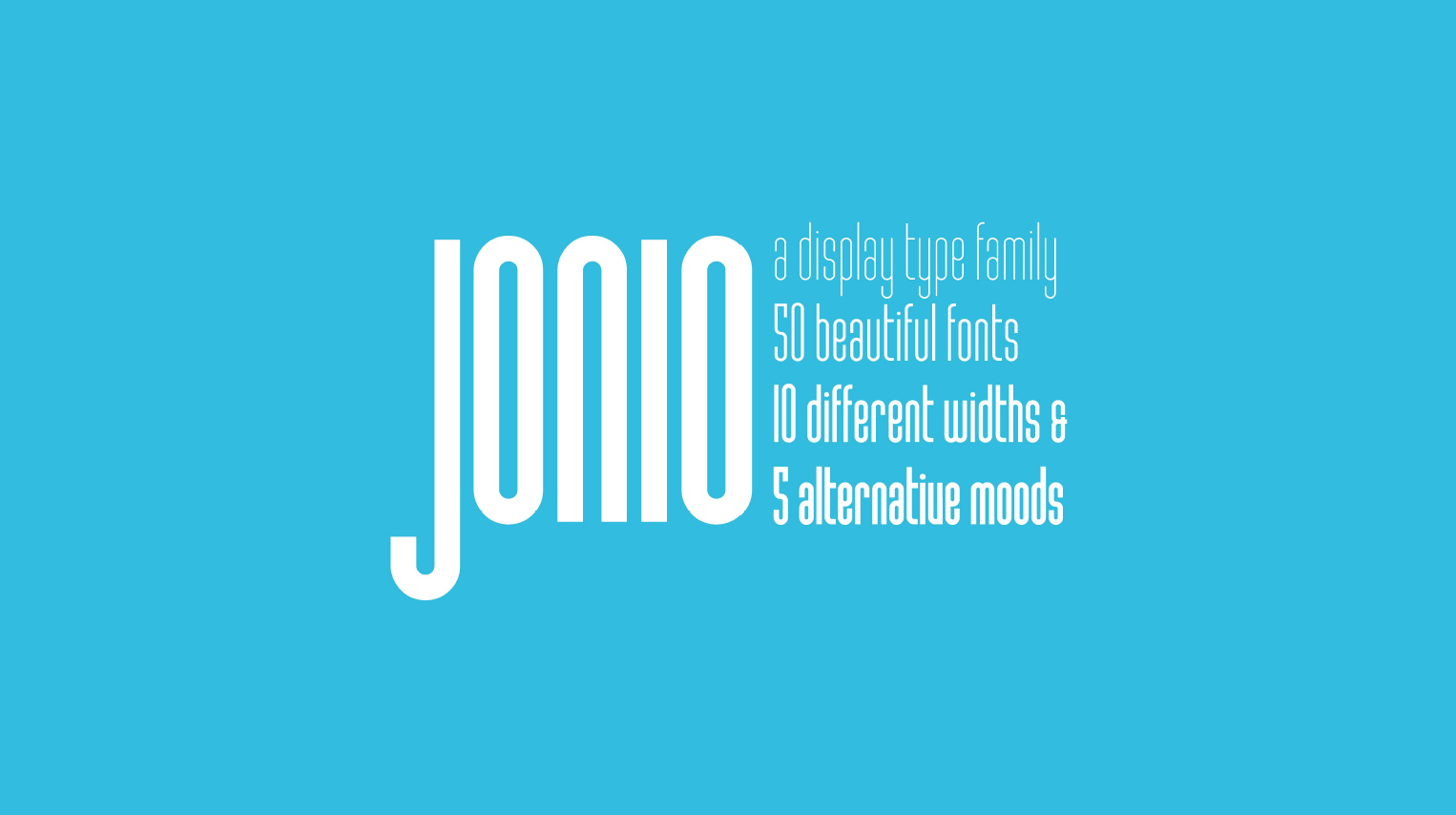
Disegnare caratteri tipografici a Firenze: un corso di tipografia e calligrafia targato IED
Circa 120 anni prima che il termine “Graphic Designer” fosse coniato, il rapporto fra carattere tipografico e le industrie editoriali raggiunse il picco. Insieme alla rivoluzione industriale, subentrarono nuovi caratteri tipografici in grado di provvedere a una specifica necessità; quella di differenziarsi in mezzo a un oceano di cartelloni e di messaggi pubblicitari.
Fino a quel momento, il carattere tipografico era progettato per uno scopo soltanto: quello di essere fruibile al meglio sui lunghi tratti di testo. Ma con la meccanizzazione e le principali innovazioni nella tecnologia di stampa (ad es. Steam Press, 1814), gli inserzionisti in particolare cercavano caratteri che si distinguessero dalla massa. Da qui, la nascita di centinaia di nuovi caratteri (in particolare decorativi e slab) che ridefinirono la concezione di caratteri tipografici conosciuta fino a quel momento storico.
Oggi l’arte del disegno delle lettere è tornata prepotentemente al centro dell’attenzione degli Artisti Visuali. La scrittura e talvolta il disegno del carattere tipografico sono infatti la componenti fondamentali in ogni progetto di design, dalla comunicazione pubblicitaria, all’editoria, al branding e al logo design.
IED, la scuola internazionale di Design, Moda, Arti Visive e Comunicazione ha creato proprio un corso di disegno del carattere (a cui io ho partecipato).
Io che avevo già un’esperienza pregressa in IED essendo laureato in Comunicazione Pubblicitaria non potevo farmi sfuggire questa fantastica occasione: partecipare all’unico corso in Italia della durata di 120 ore (tra l’altro in Formula Weekend per venire incontro alle esigenze dei professionisti).
Il corso è suddiviso in 5 moduli principali ovvero Storia e Cultura del Type Design che offre una panoramica della storia del disegno del carattere, Lettering e Disegno del Carattere che offre un’analisi approfondita delle modalità di concezione di un carattere tipografico (curato da Francesco Canovaro, Cosimo Pancini e Francesco Tartarelli di zetafonts), Calligrafia che propone come una serie di incontri laboratoriali con docenti dell’Associazione Calligrafica Italiana (Fraschesca Biasetton, Anna Schettin e Luca Barcellona) allo scopo di affrontare diverse tecniche calligrafiche alla base delle forme fondamentali di disegno del carattere, Laboratorio di Letterpress in collaborazione con la Fondazione per le Arti Grafiche il Bisonte in cui gli studenti hanno la possibilità di seguire un workshop per sperimentare le tecniche tradizionali di composizione e stampa a caratteri mobili e il Final Work ovvero la parte finale del corso dedicata allo sviluppo di una famiglia completa di caratteri tipografici, con lo scopo di applicare ad un esempio reale le nozioni di composizione, lettering manuale e disegno apprese.
Insieme a me hanno partecipato al corso tantissime figure che lavorano non solo nel mondo della grafica ma anche nel mondo del Tattoo e dell’Illustrazione poiché disegnare lettere è una cosa molto potente. Non è soltanto un feticcio di noi Graphic Designer, è qualcosa che ha un potere quasi magico. Riuscire a creare il proprio progetto grafico, qualsiasi esso sia, arricchendolo con il proprio carattere tipografico è qualcosa che da molta soddisfazione!
Il font che ho creato durante il percorso è Jonio, un font display condensed sans serif che è stato selezionato per la pubblicazione sul futuro portale ItalianType (e di cui vi parleremo a brevissimo) curato proprio da zetafonts.
Insomma, un’esperienza che non posso fare altro che consigliare a tutti!